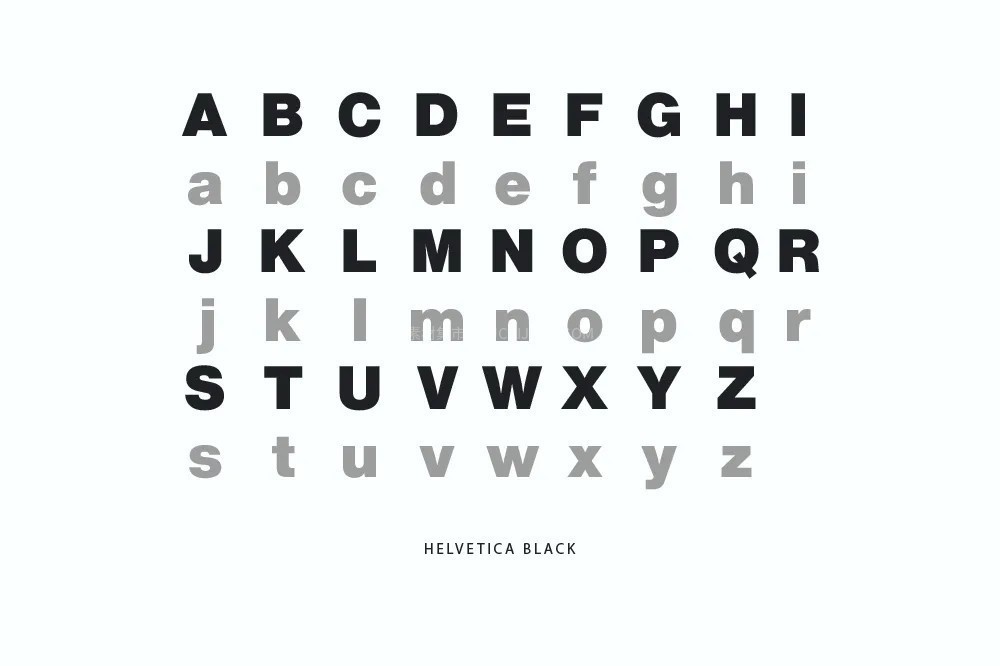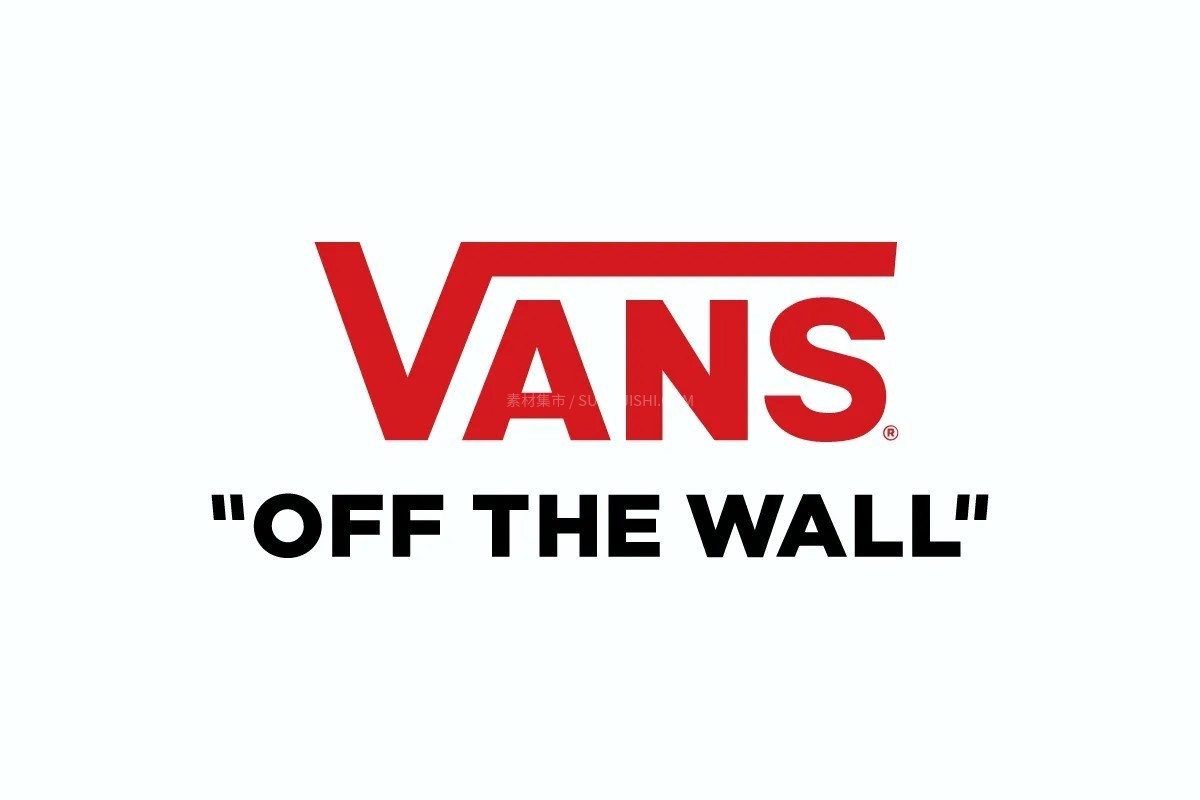
Vans经典潮牌Logo字体
Vans,这个标志性的滑板品牌,其简洁而又极具冲击力的logo设计享誉全球。Vans标志中使用的字体实际上是Helvetica Black的修改版。
Vans经典潮牌Logo字体
加宽的字母形状: Vans 标志中的字母比标准的 Helvetica 字体明显更宽更粗,给人一种大胆、有冲击力的感觉。
Vans经典潮牌Logo字体
定制的字母间距: Vans 标志中的字符间距经过精细调整,比传统的 Helvetica 字体略微紧凑一些。
细微的字母变化:对“V”和“S”等特定字母进行了巧妙的修改,使其与传统的Helvetica字体略有不同,从而造就了Vans独特的视觉形象。
从本质上讲,虽然 Vans 字体从 Helvetica 中汲取灵感,但它是一种定制创作,经过精心打造,以反映该品牌独特的个性和轻松的气质。